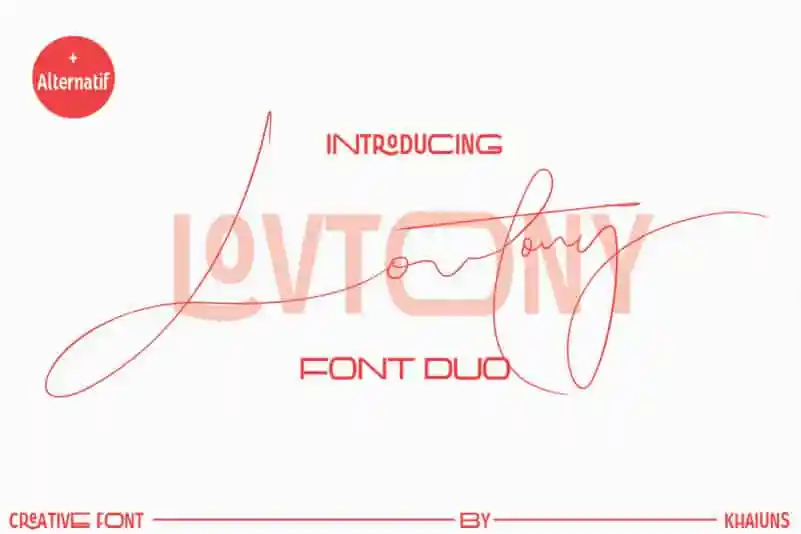
Lovtony Font Duo – Download Grátis
A fonte Lovtony Font Duo é uma dupla moderna de sans serif e script a mão com inúmeros ligantes cuidadosamente criados para se encaixarem perfeitamente um no outro. Ela oferece aos designers uma combinação sofisticada de elegante script e serif sem seraúla, que parece direcionar seu olhar em direções distintas mas sempre unindo-se com requinte. Incluindo ligaturas é particularmente útil quando você precisa criar a sensação de graça natural entre os estilos. Essa característica faz com que Lovtony Font Duo seja perfeita para criações de design, especialmente em aplicações de tipografia clássica, como editoriais de jornal, revistas e editorias de moda. Para aqueles que valorizam uma composição gráfica delicada mas forte, não há melhor opção. Com a Lovtony Font Duo, o designer tem à disposição um conjunto de fontes inconfundíveis capaz de criar ambientes estilizados e elegantes em qualquer mídia digital ou impressa.